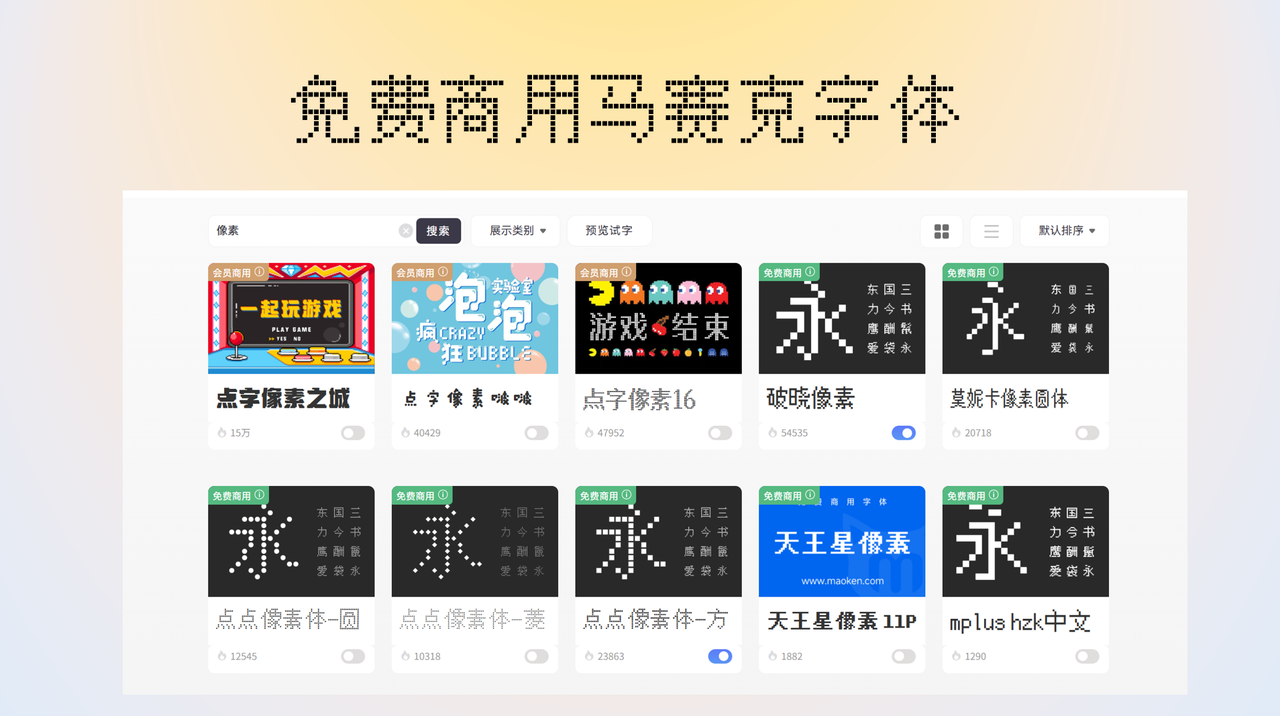
免费商用马赛克字体下载推荐:4个靠谱平台分享
前段时间我在做一个复古风格的海报设计,客户希望标题能有那种像素游戏的感觉,我第一反应就是找马赛克字体。但翻遍了电脑里的字体库,发现要么风格不对,要么就是不确定能不能商用。
本文给大家介绍几个可以免费下载马赛克字体的平台,以及几款我常用的马赛克字体
字由平台里的马赛克字体资源
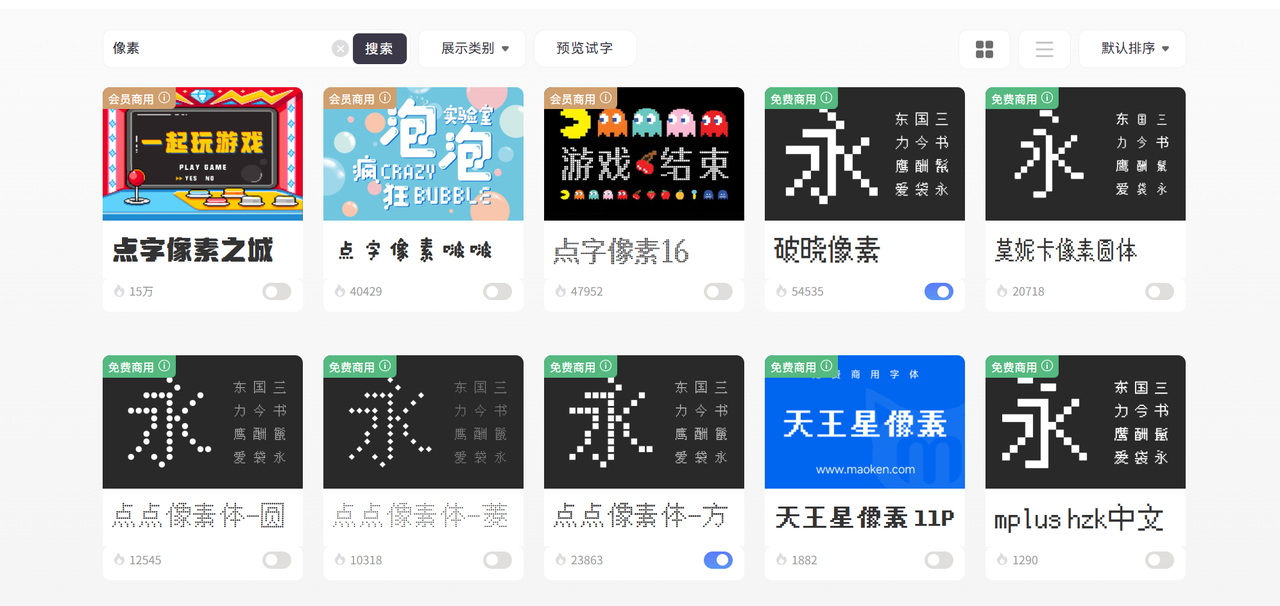
我常用的几款马赛克字体
- 点字像素之城
- 点字像素啵啵
- 点字像素16
- 破晓像素
- 莫妮卡像素圆体
其他三个我常用的字体下载平台
除了字由,我还会在其他几个平台找字体资源,尤其是需要更多样化的马赛克风格选择时。
Google Fonts
我之前做一个游戏主题的网页设计时,就在 Google Fonts 上找到了一款叫「Press Start 2P」的像素字体,这款字体完美还原了老式游戏机的感觉,笔画粗壮、辨识度高。Google Fonts 的好处是可以直接嵌入网页,通过 CSS 引用,不用下载安装,对做 Web 设计的人来说特别方便。
DaFont
DaFont 是一个老牌的免费字体网站,收录了大量独立设计师上传的字体,风格非常多样。我在找一些比较小众或者风格特殊的马赛克字体时,经常会来这里翻。
这个平台上有个「Bitmap」分类,专门收录像素和点阵字体,我在这里找到过很多有趣的马赛克字体,比如那种带霓虹效果的像素字体,或者故意做得有些破损感的复古马赛克字体。这些字体用在创意海报或者音乐专辑封面上效果很棒。
猫啃网
对于需要中文马赛克字体的人来说,猫啃网是个不错的选择。它收录了一些开源的像素中文字体,比如「袖珍像素体」「乐米像素体」这些,虽然数量不算特别多,但质量都挺高,而且中文显示效果比直接用英文像素字体好很多。